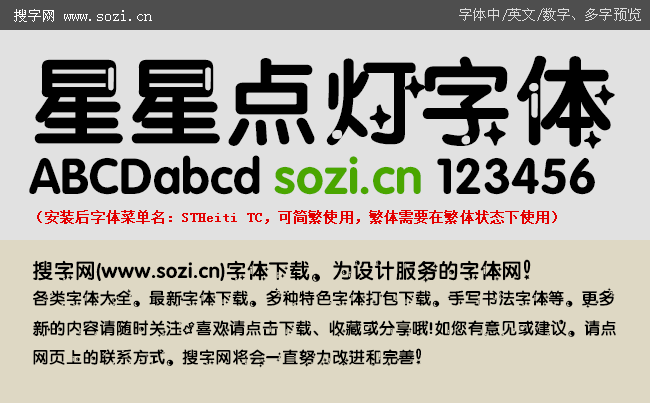
星星點(diǎn)燈字體
搜字網(wǎng)給大家提供一款很有趣的手機(jī)中文字體下載。修改者給他起名為星星點(diǎn)燈字體,這款手機(jī)字體是在粗圓體字體為原形,筆畫間點(diǎn)綴了可愛的卡通星星圖案。在具備粗圓字體醒目清晰端正的風(fēng)格同時(shí),卡通味也特別濃,是一款非常可愛的卡通字體,特別適合喜歡手機(jī)字體個性一些的朋友在手機(jī)上安裝使用。